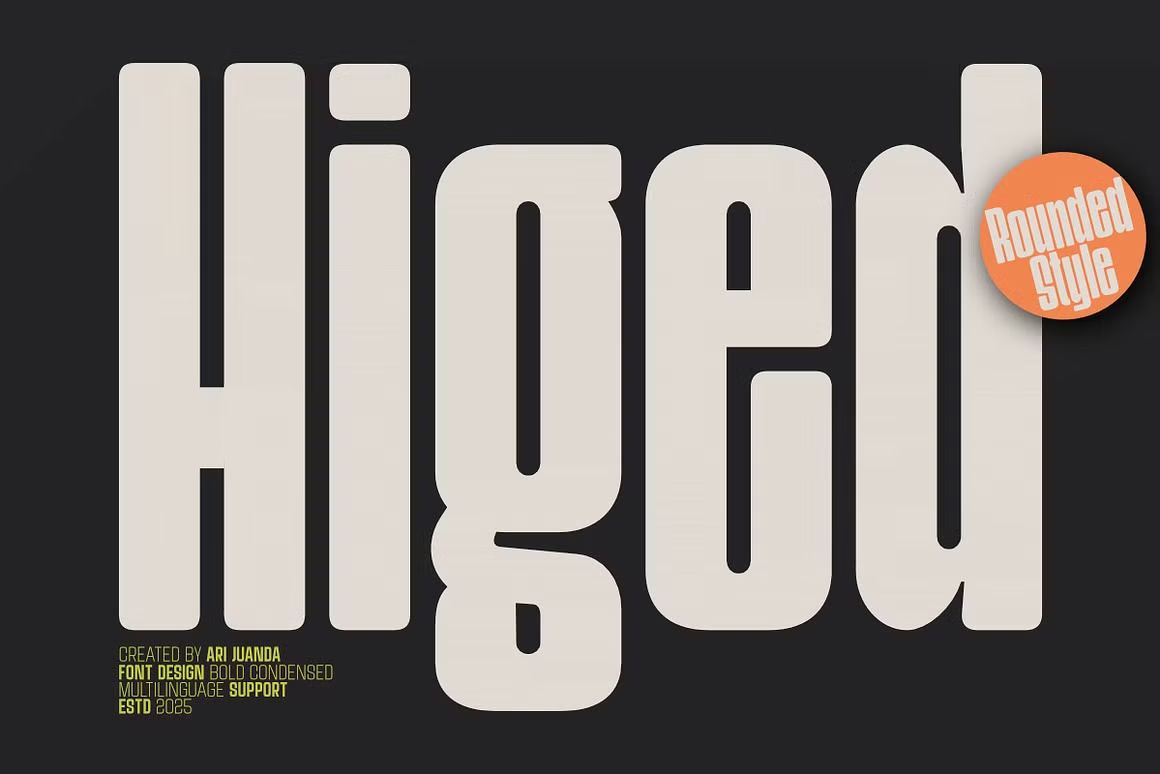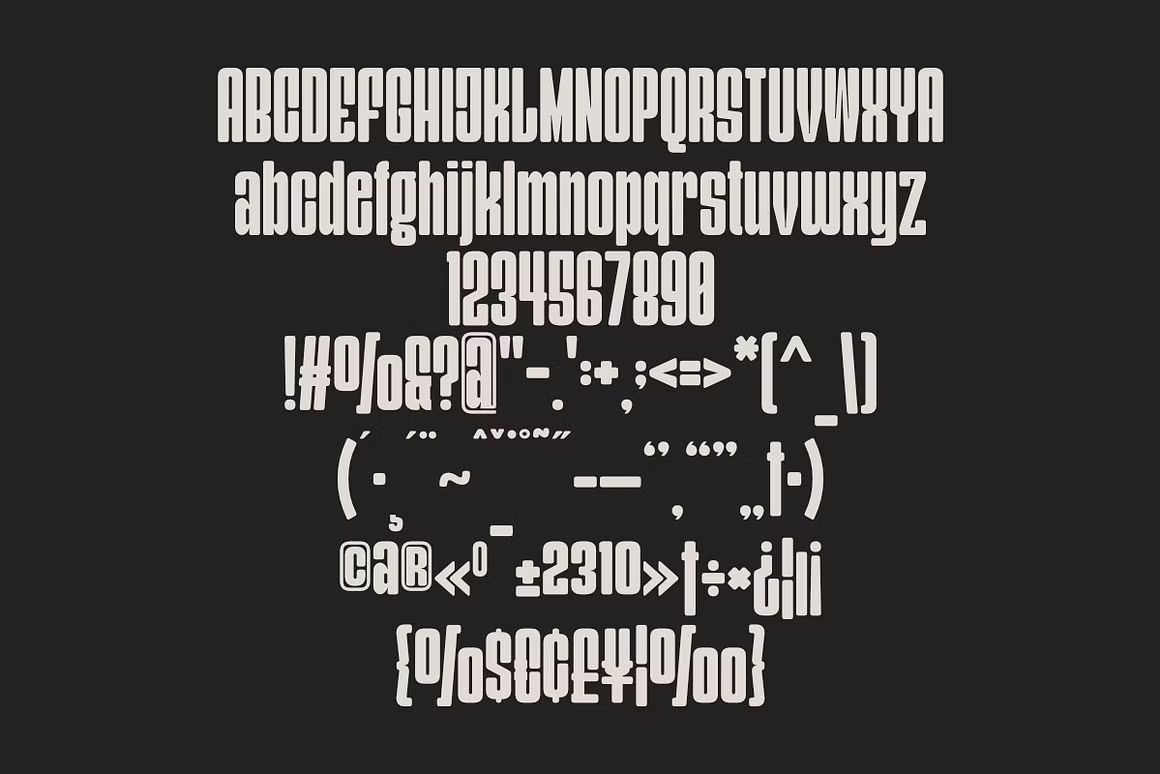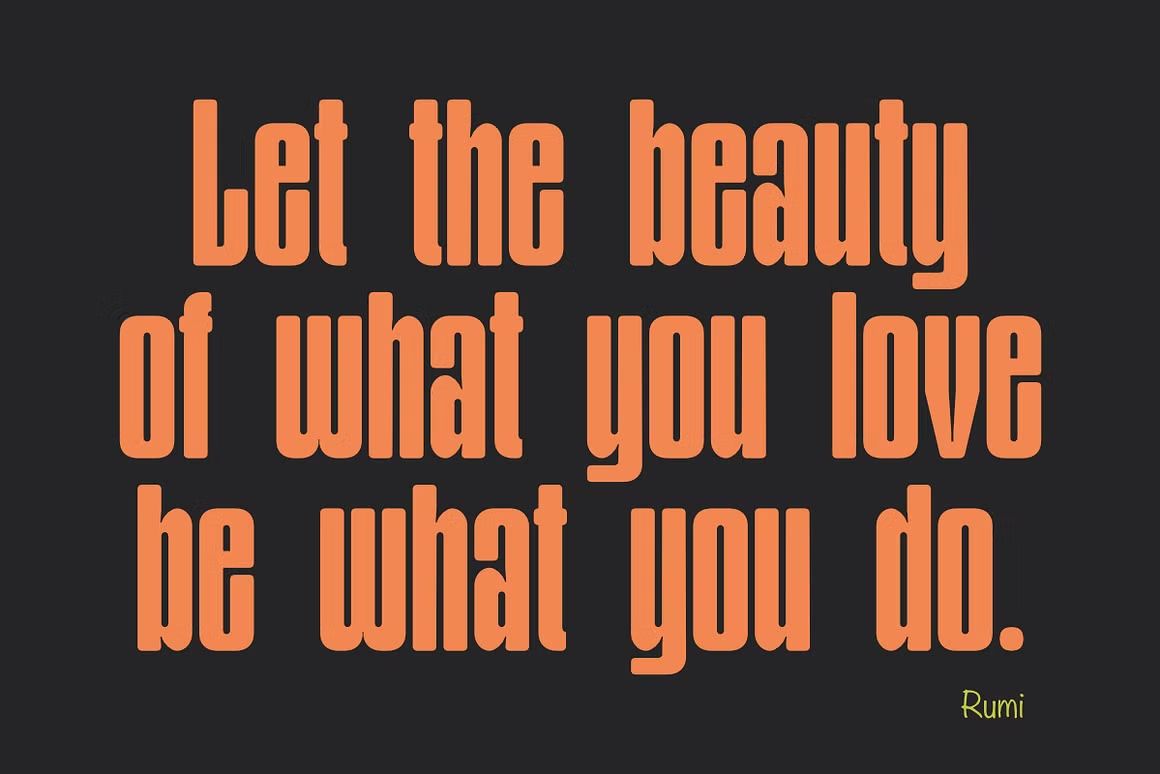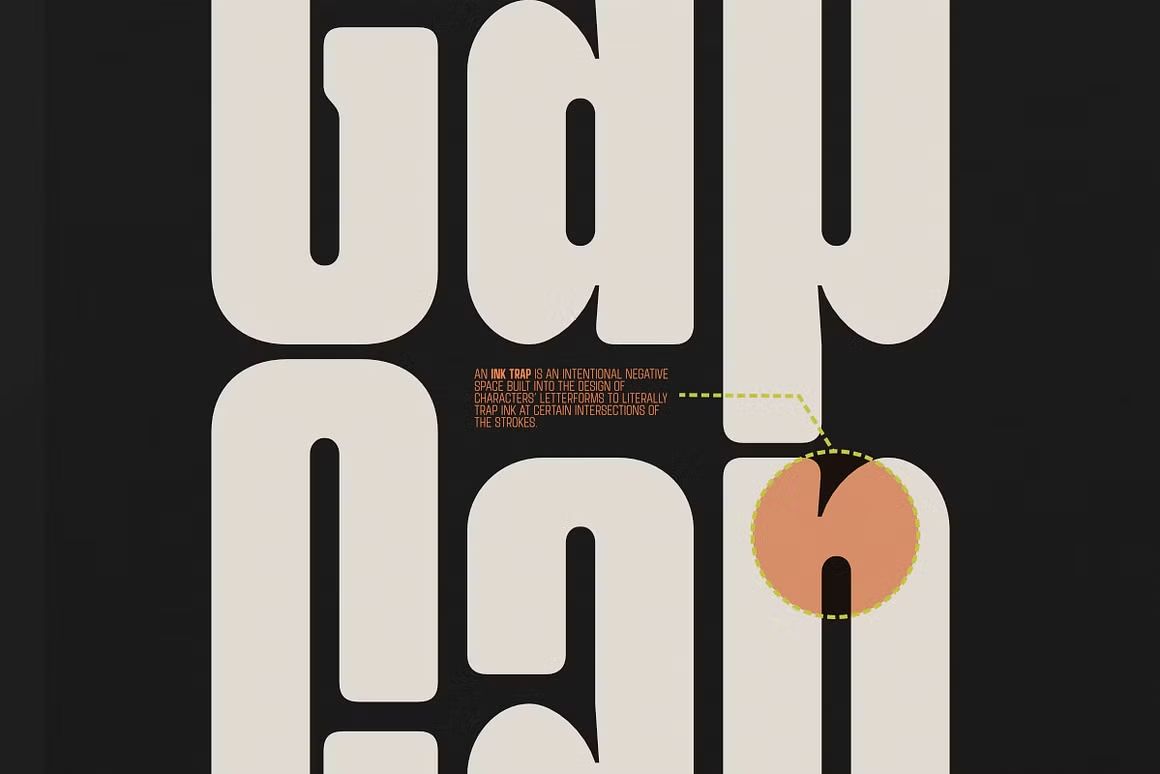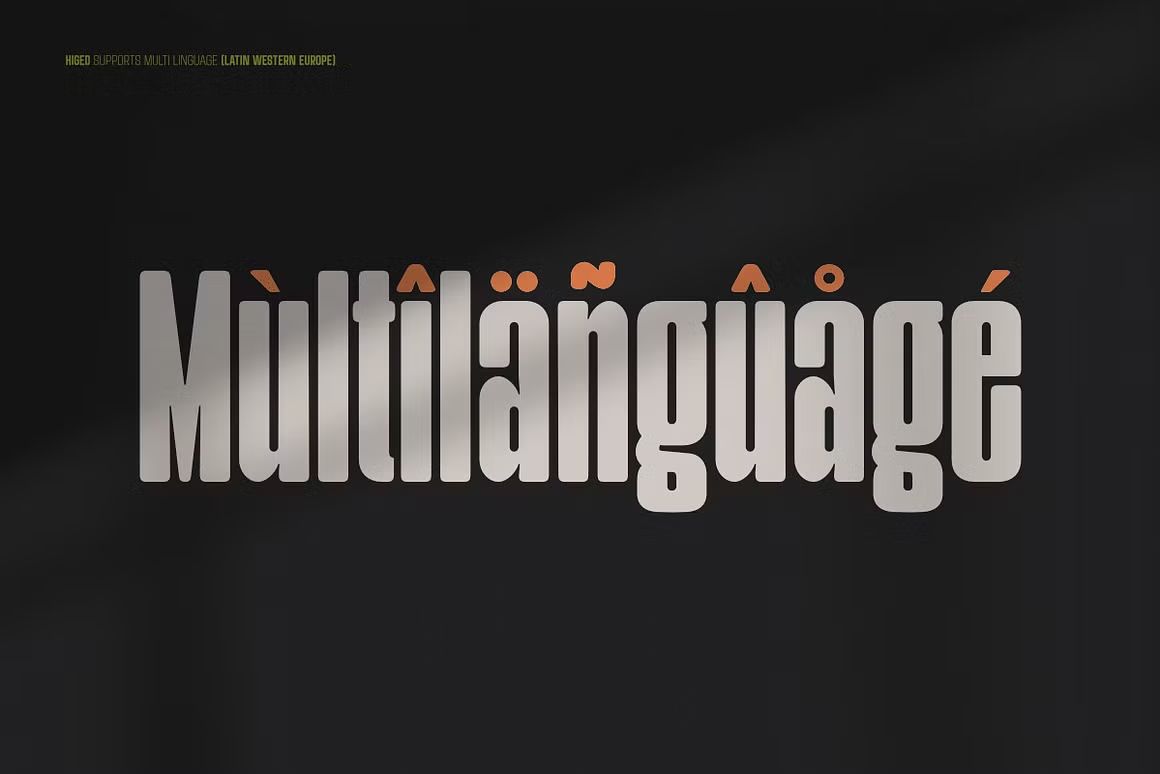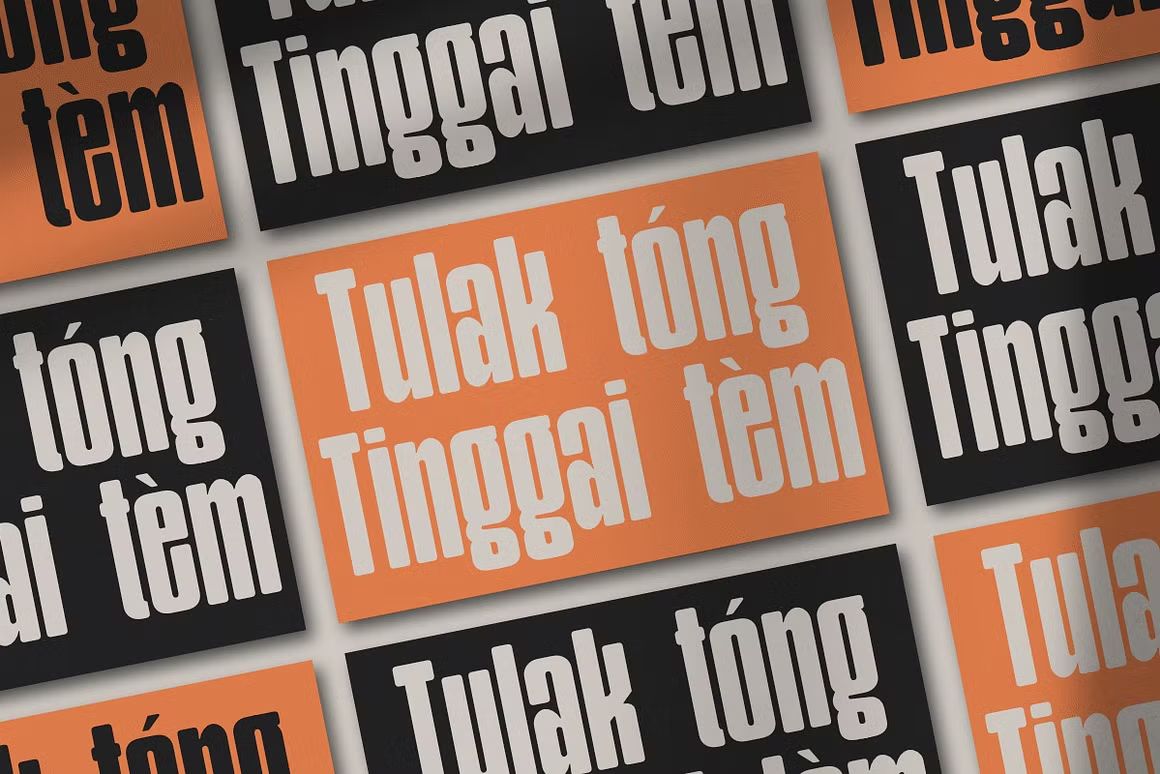
Higed – Sans Serif Font
Higed adalah font sans serif dengan desain modern dan tegas, ideal untuk proyek branding, logo, poster, dan desain digital yang membutuhkan tampilan minimalis dan profesional.
Higed adalah font sans serif dengan desain modern, tegas, dan bersih, yang memberikan kesan minimalis dan profesional. Dengan karakter huruf yang jelas dan proporsi yang seimbang, Higed sangat cocok untuk berbagai proyek desain seperti branding, logo, poster, dan materi digital lainnya yang mengutamakan kesederhanaan dan elegansi.
Fitur unggulan:
• Desain sans serif modern dengan tampilan minimalis dan tegas
• Cocok untuk branding, logo, poster, dan desain digital
• Termasuk huruf besar, huruf kecil, angka, dan simbol lengkap
• Ideal untuk proyek cetak maupun digital yang membutuhkan tampilan bersih dan profesional